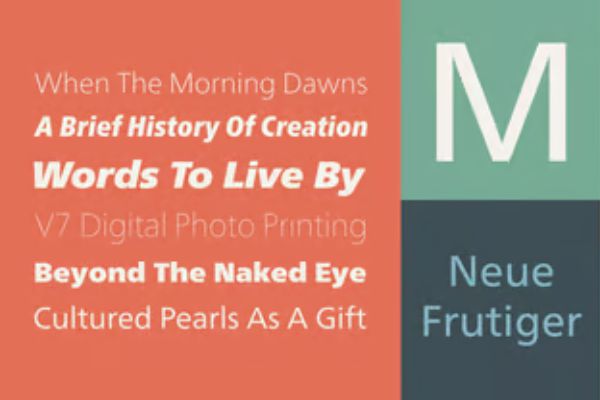
Neue Frutiger® Pro Condensed Thin
Neue Frutiger 对 Frutiger 进行了修订和改进,但相比 Frutiger Next 又回归了原始设计。它与原来的 Frutiger 系列完美契合,并增强了现有的字重和风格。Neue Frutiger 也非常适合与 Frutiger Serif 一起使用。